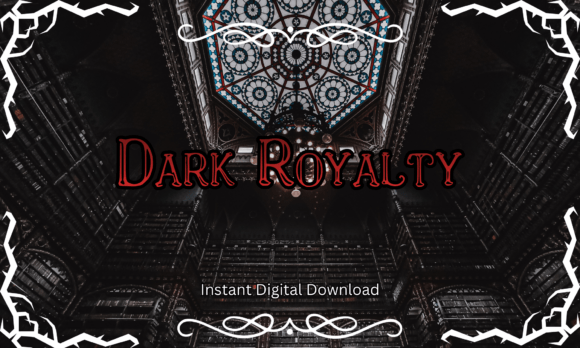
Dark Royalty
適切なデザイン要素を見つけるのは難しい場合がありますが、Dark Royaltyは作品を即座に引き立てる優れたコレクションを提供します。
POD(オンデマンド印刷)製品、結婚式の招待状、またはソーシャルメディアのグラフィックを作成している場合でも、Dark Royaltyは理想的です。